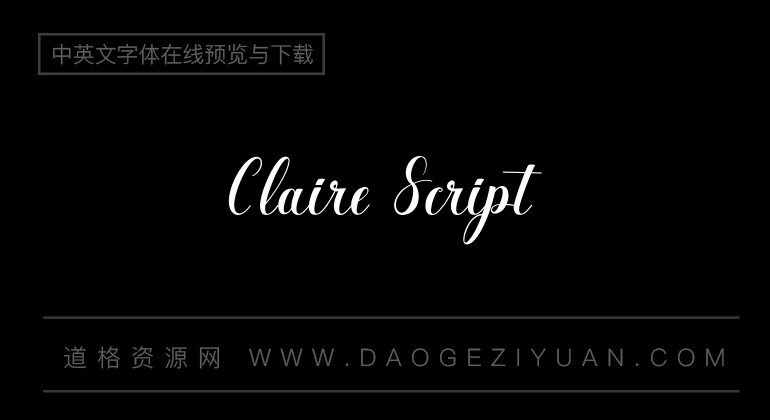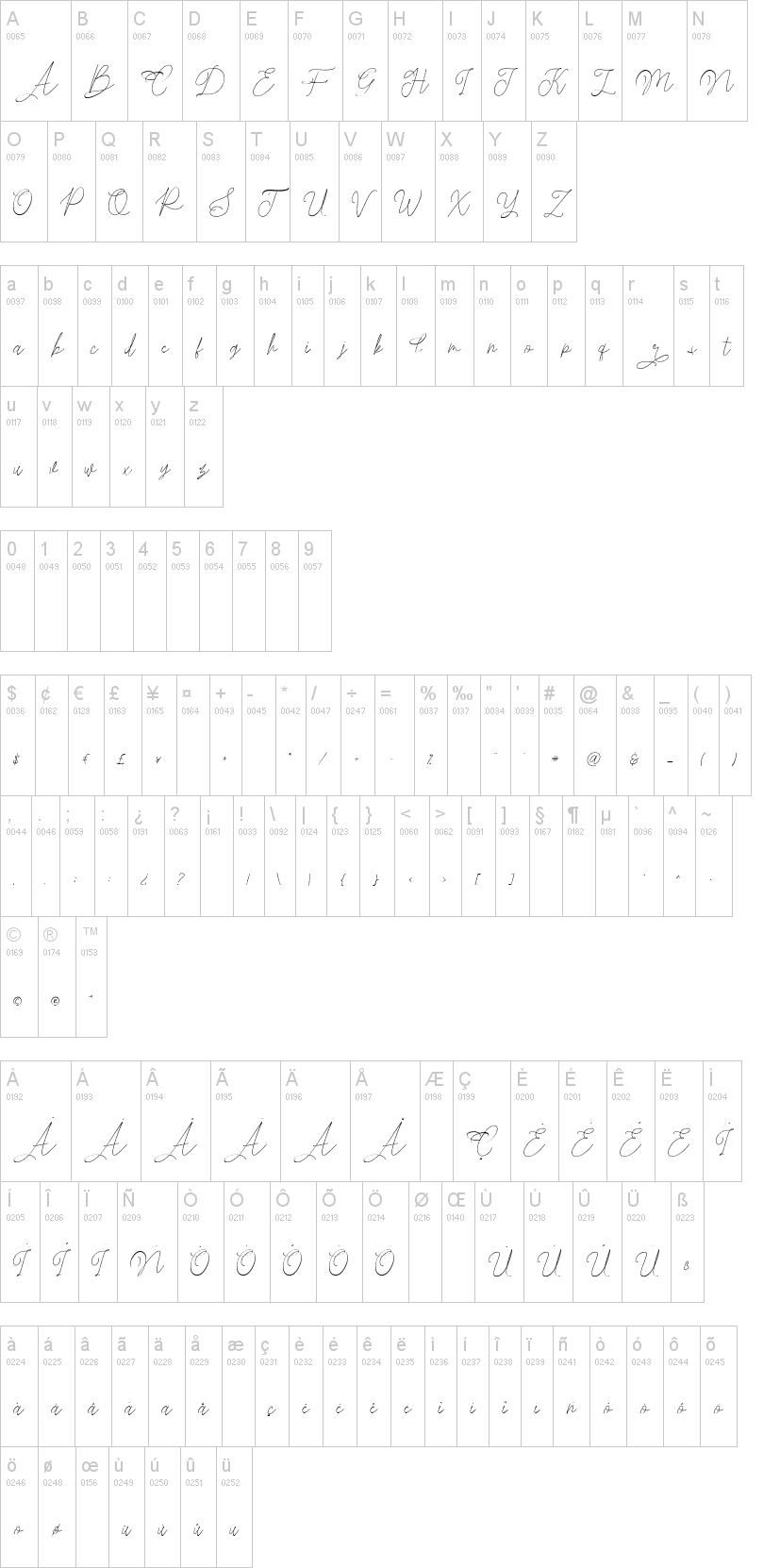
Claire Script
Claire Script是一款古典风格的手写字体,由美国设计师Mandy Greer设计。它的特点是自然的曲线和细节,表达出一种令人难以置信的精细感和温暖感。它可以用于商业、个人和家庭项目,是一款非常适合多种用途的字体。Claire Script字体有着独特的风格,既可以用于报纸、杂志和书籍,也可以用于网页、海报和广告。
Claire Script是一款非常不错的手写艺术字体,具有很好的视觉感,适合于文化类的宣传设计、商业类品牌的广告和产品包装设计以及个性化文字排版等较多场景。